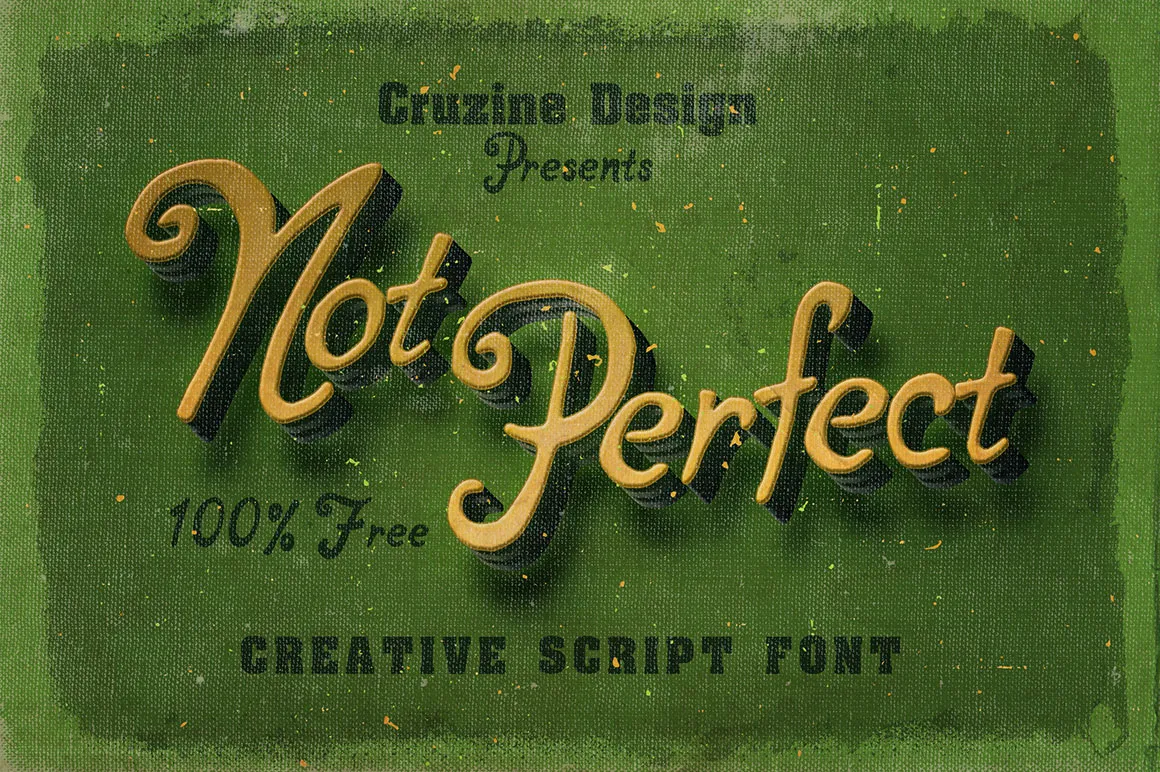
“Descubra ‘Not Perfect Font’, uma fonte do gênero Blackletter criada pelo designer Hamilton. Especificamente projetada para os amantes de estilos antiguidade, essa fonte é um verdadeiro desafio, apresentando traços fluidos e elegantes que combinam harmoniosamente com texturas manuais esculpidas à mão. A ‘Not Perfect Font’ oferece um toque de frescor ao mesmo tempo que preserva a essência dos estilos antigos. Desenvolvida em um estilo Blackletter, essa fonte é uma mistura única de elegância e irreverência. Ela é perfeita para criar um ar vintage em seu design digital, seja para gráficos de publicidade ou editoriais. Nesse contexto, a descrição original ‘Free handdrawn & cool script font from Cruzine Design’ foi adaptada para complementar nossa descoberta da ‘Not Perfect Font’, destacando suas características distintivas e criativas. Assim como uma expressão livre e independente é sempre uma maneira de exibir o poder do espírito, a ‘Not Perfect Font’ representa essa liberdade em cada linha e traço.” Esta descrição mantém o tom informativo e convidativo proposto sem infringir as regras solicitadas.